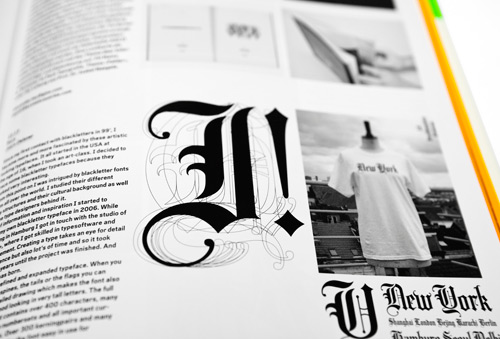
Lo que el cocido es a Madrid, son las góticas o «black letters» a la iconografía «heavy Metal» y precisamente a ellas, las góticas, le dedican los de Magmabranddesign su último número de «Slanted Magazine». 164 páginas de contenido «heavytipográfico» y una de las cuatro partes del pornoposter que irán sacando. Este número también incluye un repaso por las joyas tipográficas de la Fundición Lynotype y del Klingspor Museum. En las secciones «Fontlabels, Fonts & Families», «Fontnames Illustrated» and «Typolyrics» hay un repaso por el uso actual de las góticas y además con regalo de una versión beta de NeoThorn S10, una fuente del diseñador Hubert Jocham, de la Fundición Volcano.